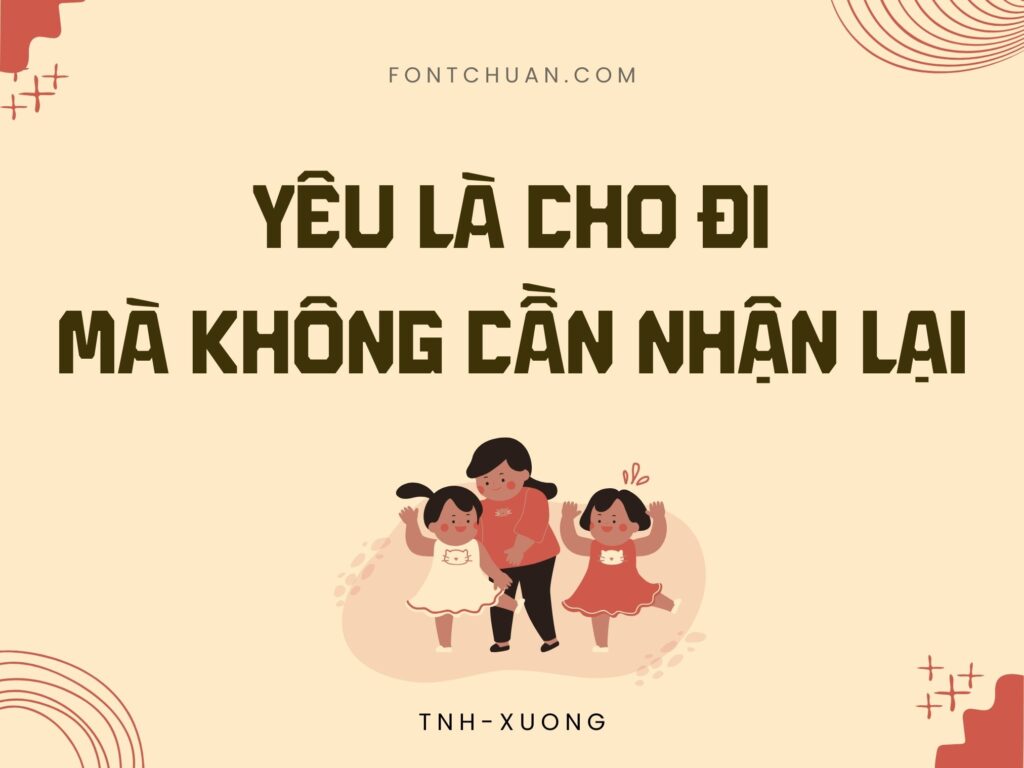
Font Xuồng Font Tiếng Việt
TNH Xuong là một kiểu chữ sans-serif được thiết kế bởi Trương Nguyên Huy, lấy cảm hứng từ “Xuồng Ba Lá” — một phương tiện di chuyển truyền thống trên sông của người dân miền Tây Nam Bộ Việt Nam. Font này có các nét chữ đậm, chắc chắn, tượng trưng cho những tấm ván gỗ được nối kết với nhau, mang lại cảm giác thủ công và mộc mạc. TNH Xuong hỗ trợ đầy đủ tiếng Việt và nhiều ngôn ngữ khác, được sưu tầm và đăng bởi thành viên của Font Chuẩn.
Bên cạnh đó, TNH Xuong cũng có thể được sử dụng như một Font chữ công nghệ, phù hợp cho các dự án thiết kế hiện đại, giao diện số, tài liệu kỹ thuật hoặc các sản phẩm công nghệ, mang lại vẻ mạnh mẽ và dễ đọc.
Font có thiết kế chữ in hoa đồng nhất với chữ thường, theo phong cách ALLCAPS, rất phù hợp cho các tiêu đề, poster, biển hiệu và các ấn phẩm truyền thông cần sự nổi bật và cá tính. Ngoài ra, cho những thiết kế mang không khí lễ hội, vui nhộn, Font chữ Halloween này là lựa chọn lý tưởng với các họa tiết đặc trưng như mạng nhện, dơi, bóng ma, giúp TNH Xuong và font này kết hợp tạo nên sự độc đáo, sinh động cho các sự kiện như lễ hội, sinh nhật, ngày Nhà giáo hay Valentine.